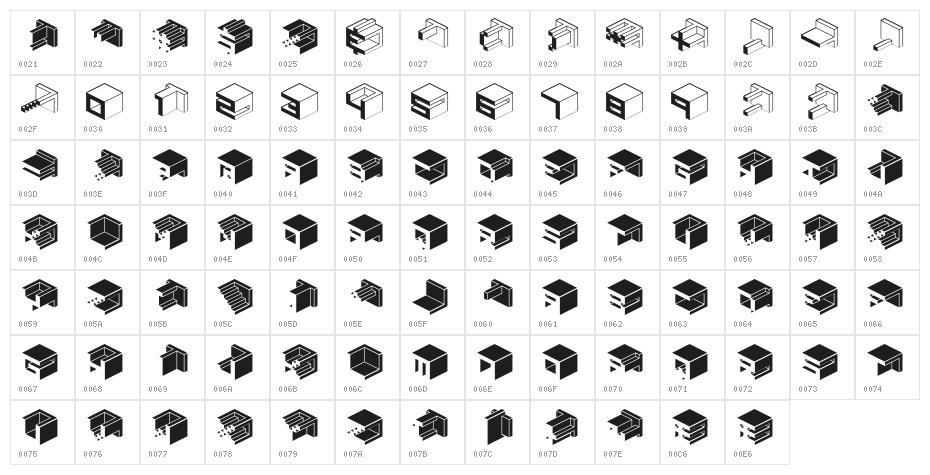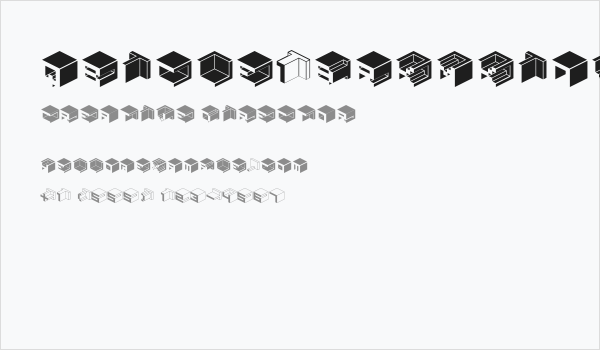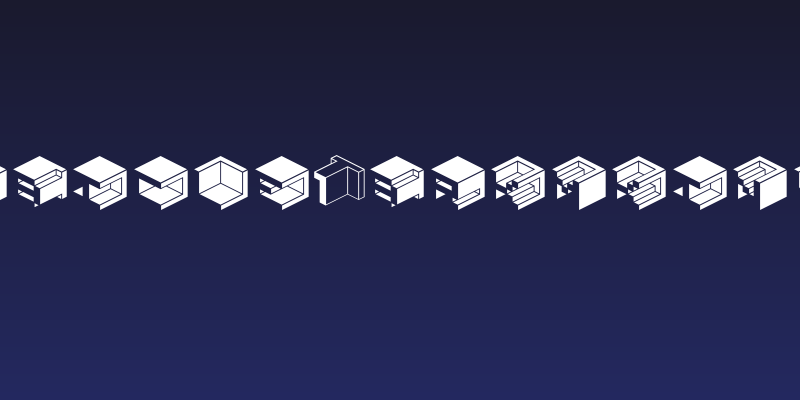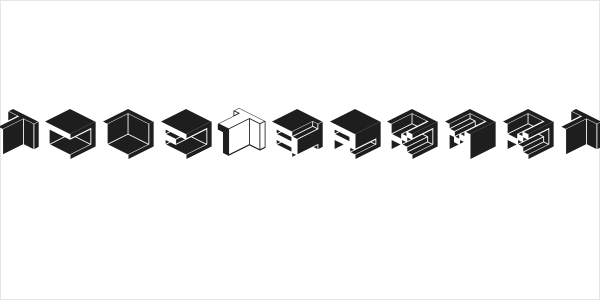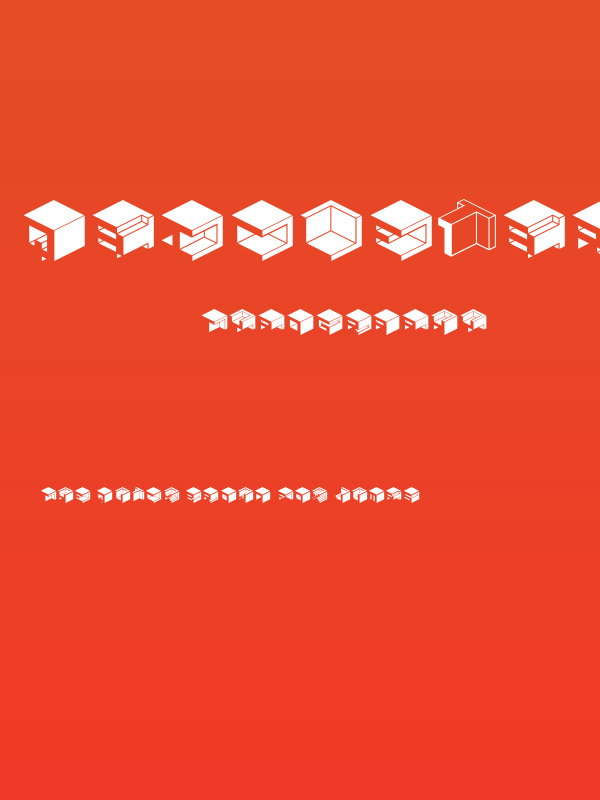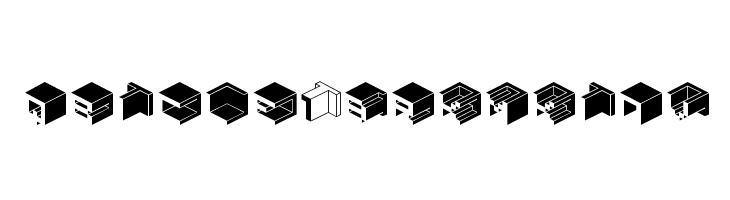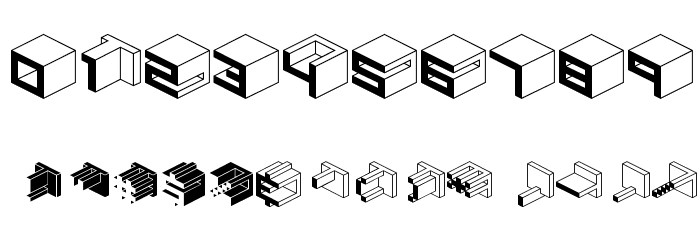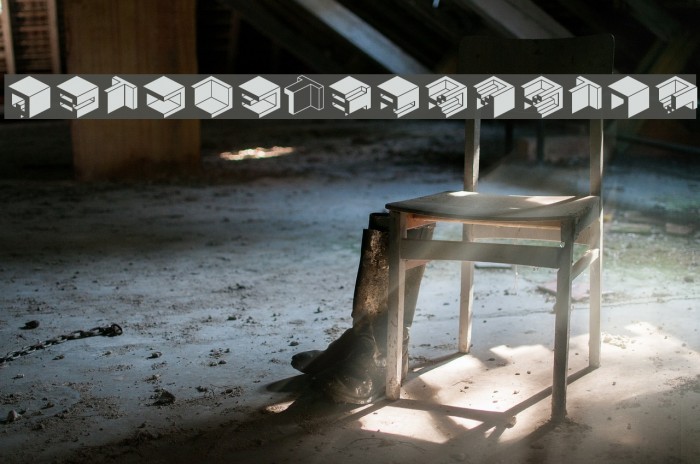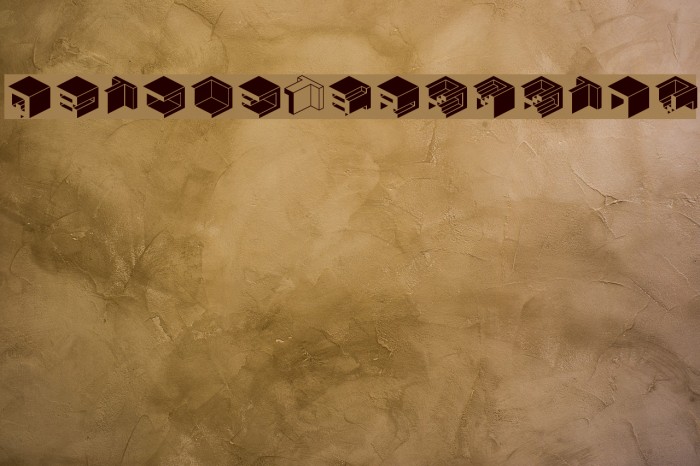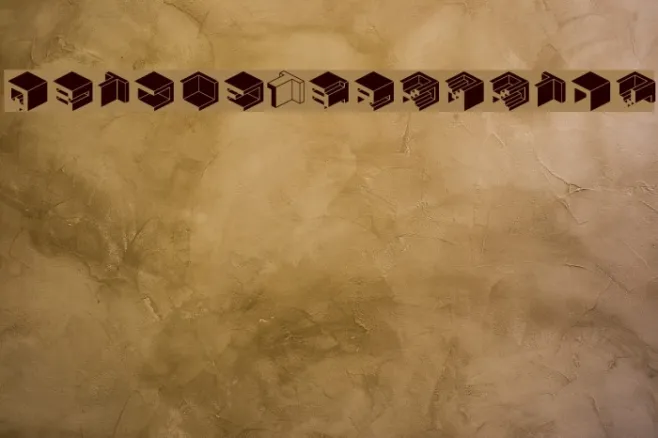
Qbicle1BRKMKinv Font
| Projets proposés | Ideal for architectural branding, futuristic designs, tech-related projects, and innovative advertising campaigns. |